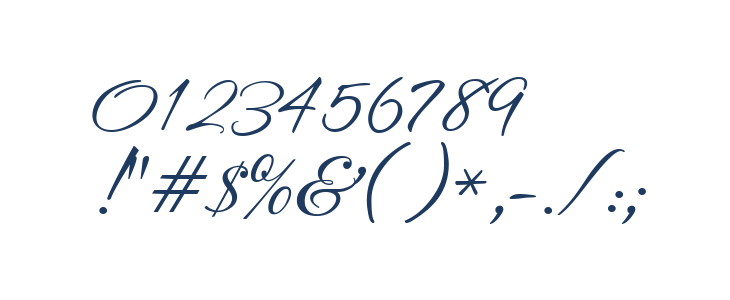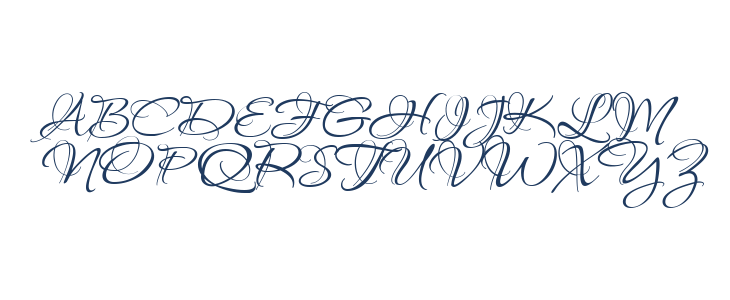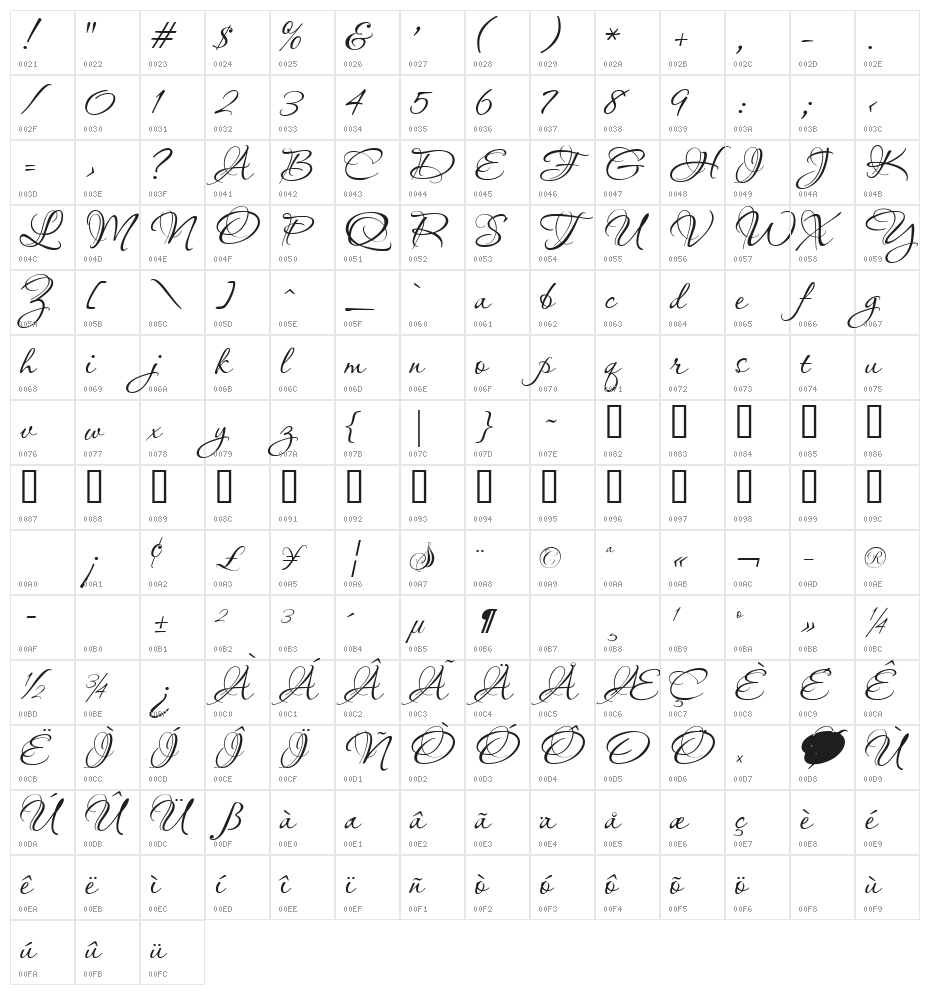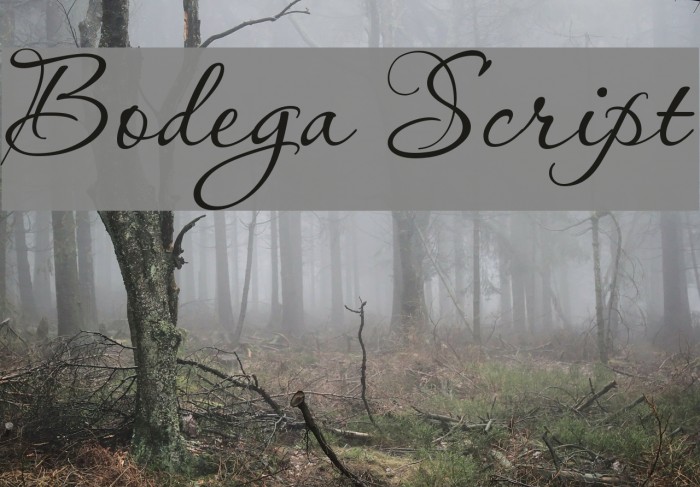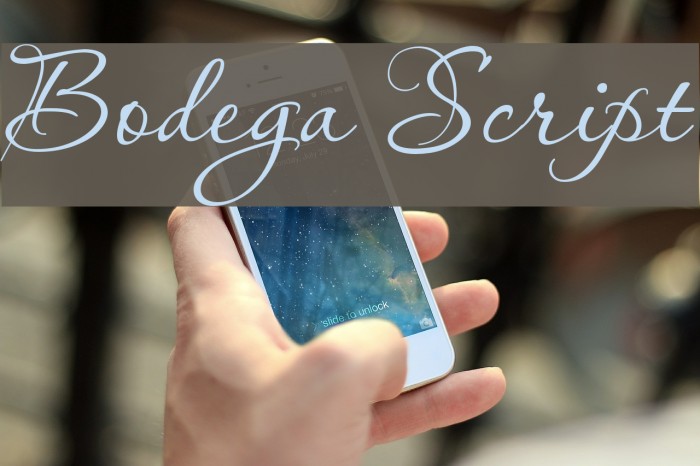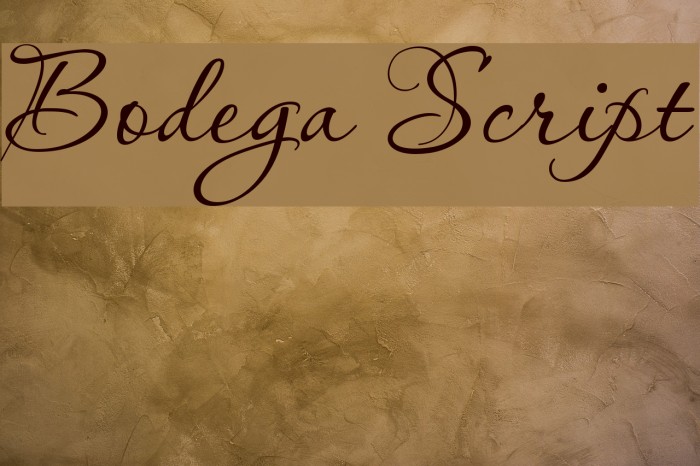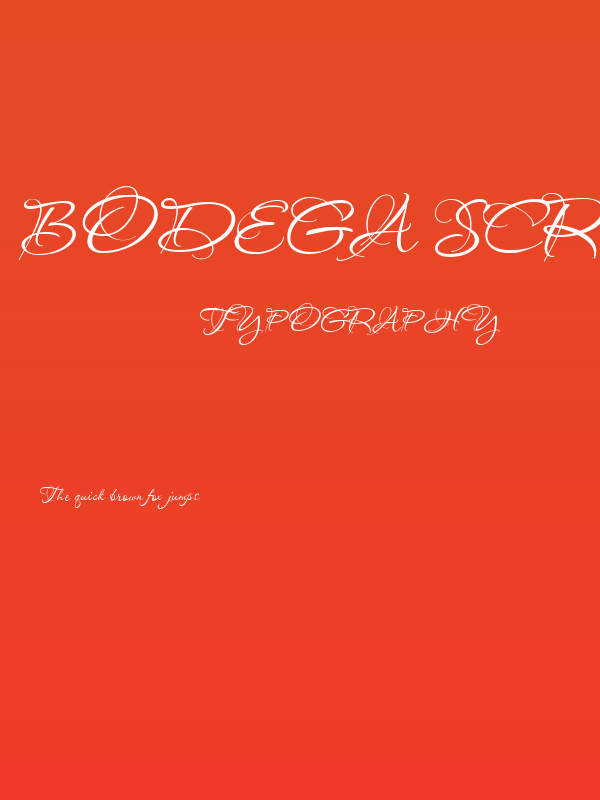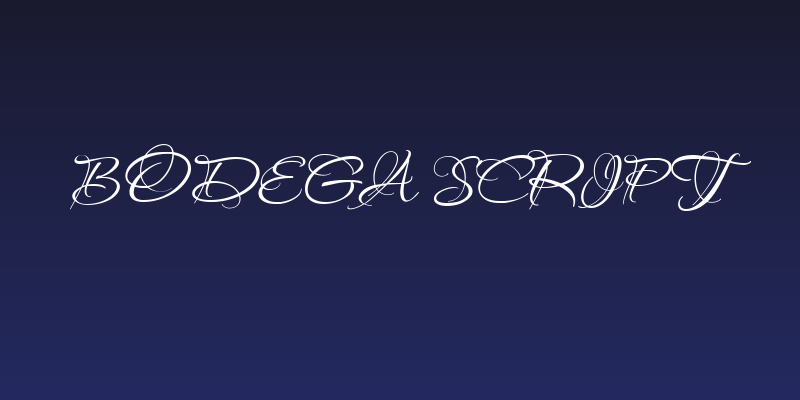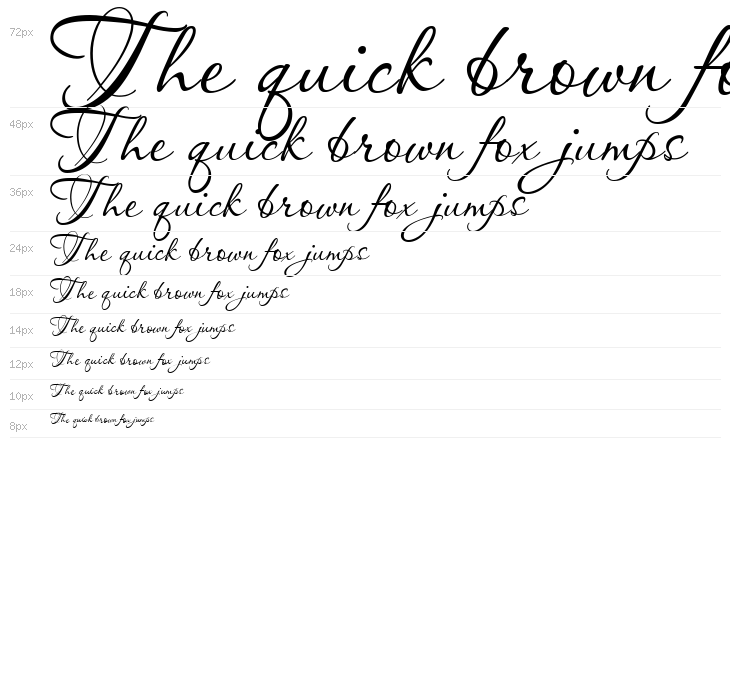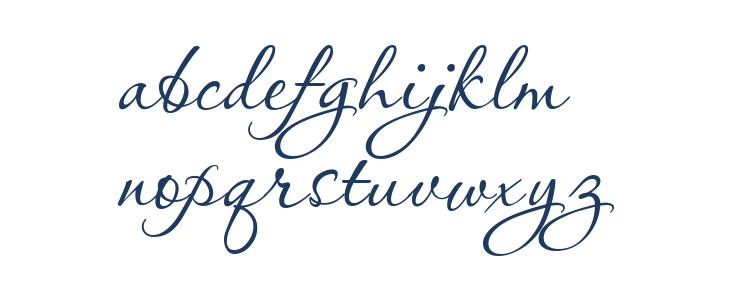
Bodega Script Font
| Stile generale | Elegant, Artistic |
| Caso d'uso | Logos, Invitations, Decorative text |
| Progetti proposti | Ideal for wedding invitations, elegant branding, and artistic projects. |